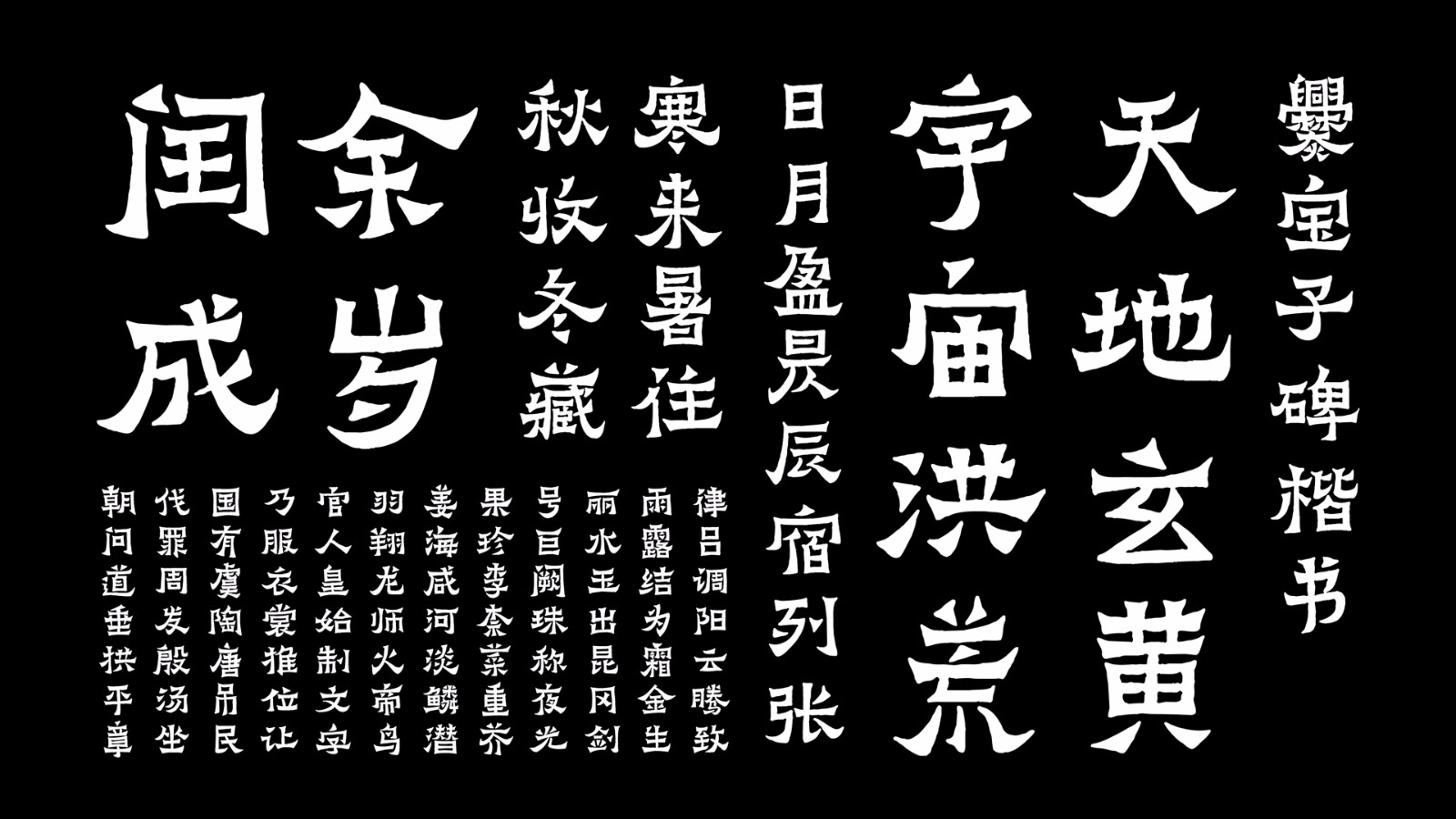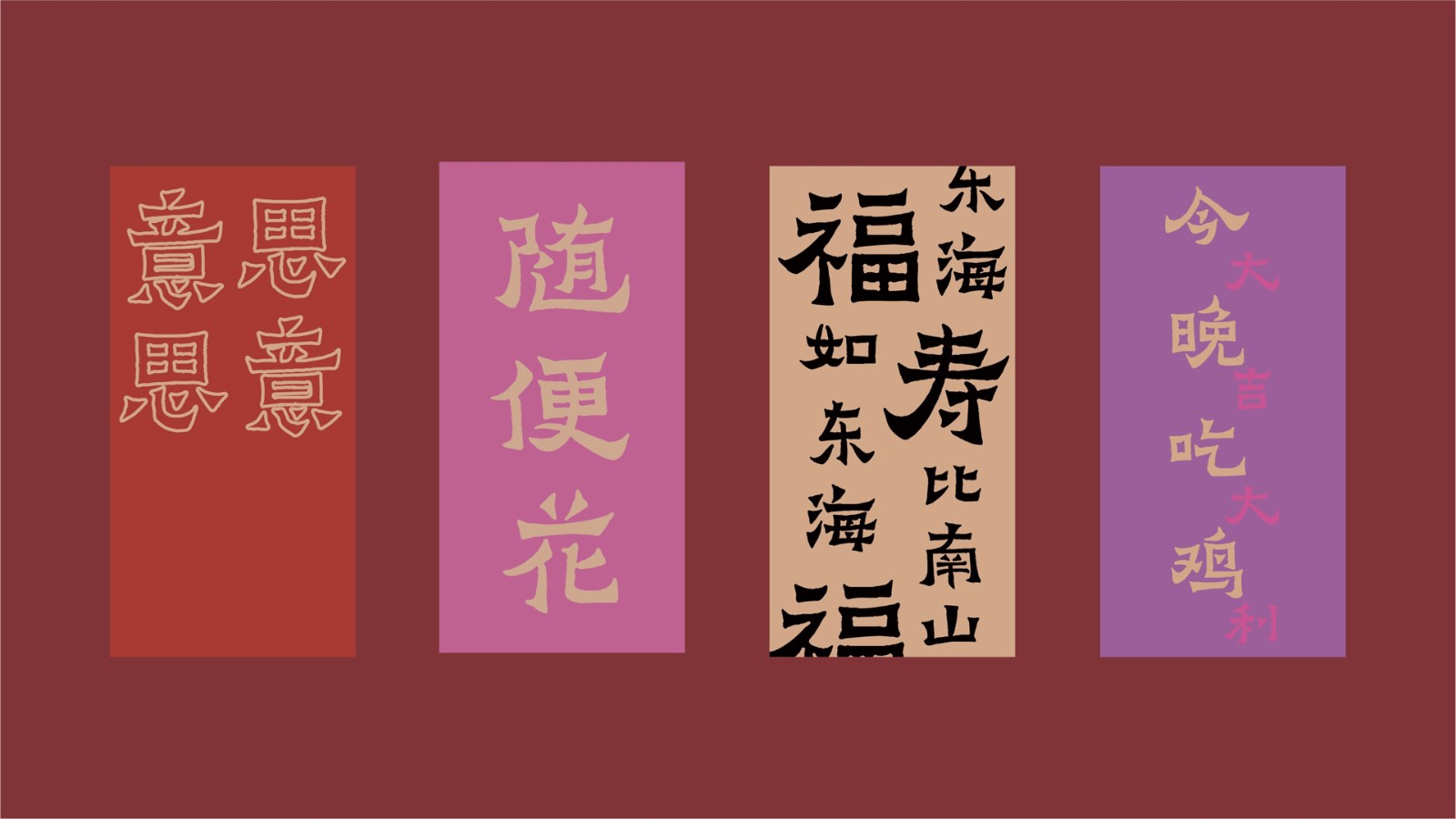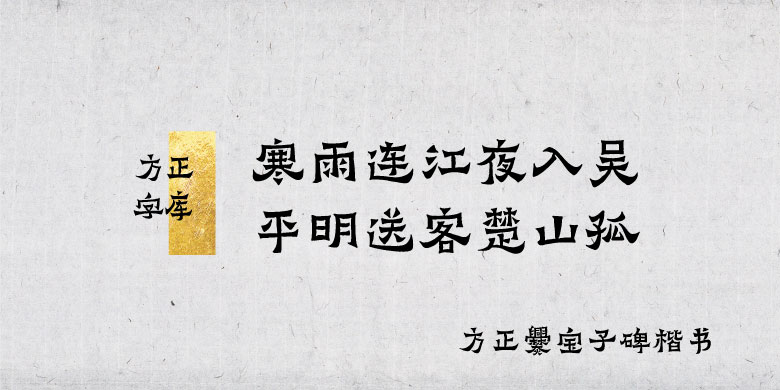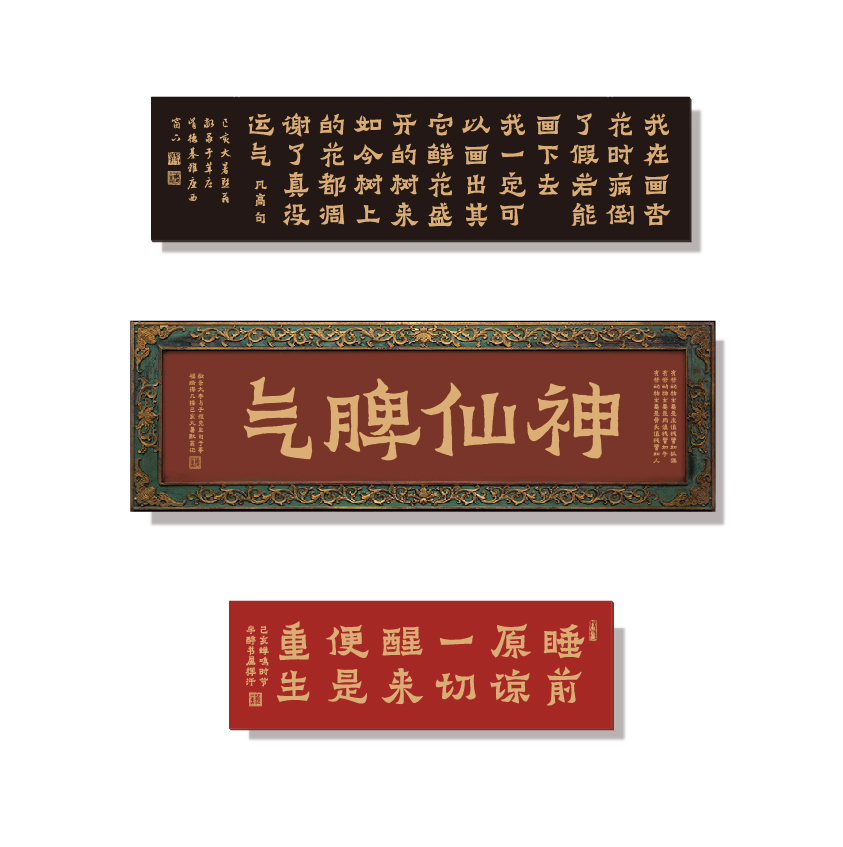
方正爨宝子碑楷书
字体品牌: 方正字库 中华精品字库 整理/设计:苏新诗,汪文 字体分类:楷书、爨体 字体属性:精品字 字符集:简繁扩展(GBK)、大陆简体(GB2312-80) 发布时间: 2019
爨宝子碑 东晋碑刻,正书,碑额题“晋故振威将军建宁太守爨府君之墓”。义熙元年(公元405 年,此时已改年号为义煕,或因边陲闭塞,故书碑人仍依旧年号写作“大亨四年”)立。清乾隆四十三年(1778 年)在云南曲靖南七十里扬旗田出土,道光十五年(1835 年)《云南通志》始著录,咸丰时移置城中武侯祠。书体在隶楷之间,可见文字由隶书演变为正书过程中的一种风格。
字体特征:以《爨宝子碑》为字形开发依据。朴茂古厚,大巧若拙,率真硬朗,气魄雄强,奇姿尽现,浑然天成。体势情趣、情态均在隶楷之间。
国博文物:爨宝子墓碑拓片